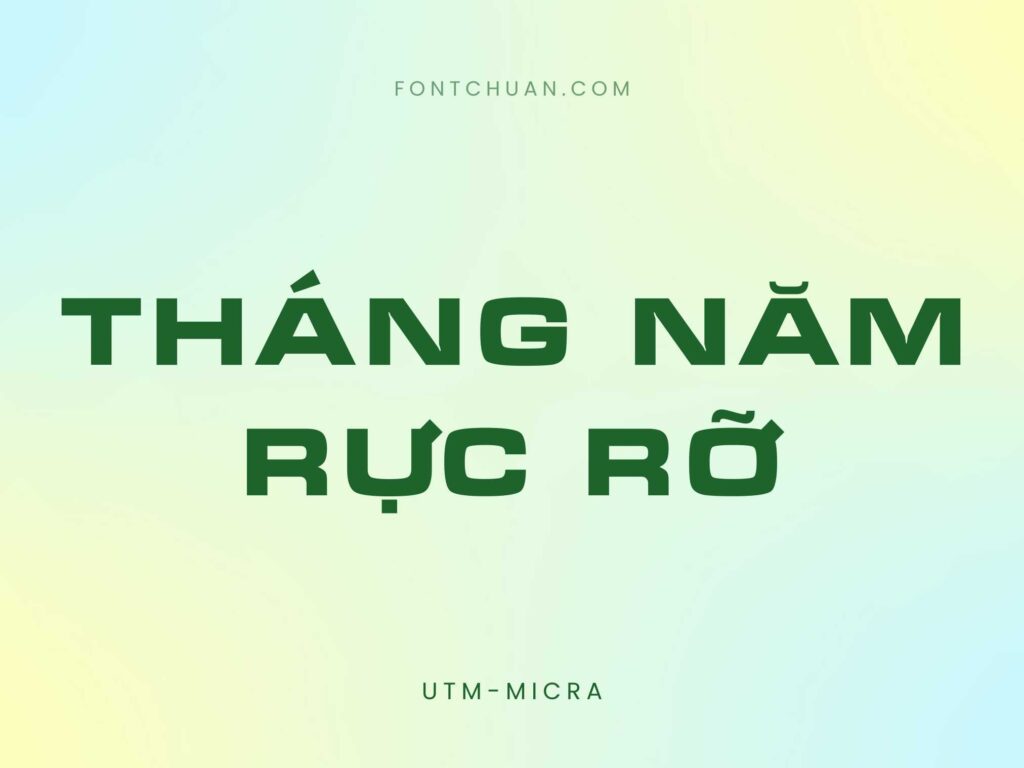
UTM Micra là một font chữ hiện đại, mang phong cách mạnh mẽ và gọn gàng, phù hợp với các thiết kế chuyên nghiệp và sáng tạo. Font này có hình thức đơn giản nhưng vẫn tạo được điểm nhấn với các đường nét rõ ràng và cân đối. Font đã được Việt hóa bởi Thiên Minh, hỗ trợ đầy đủ tiếng Việt cùng hơn 200 ngôn ngữ khác, giúp mở rộng khả năng ứng dụng trong nhiều lĩnh vực thiết kế. Thành viên của Font Chuẩn đã sưu tầm và giới thiệu font này nhằm đáp ứng nhu cầu bạn đọc, cung cấp nguồn tham khảo chất lượng và ứng dụng thực tế vào các dự án thiết kế
Về đặc điểm thiết kế, UTM Micra có cấu trúc chữ cân đối, độ dày đồng đều và phong cách tối giản. Font này phù hợp với nhiều ứng dụng như thiết kế logo, tiêu đề, poster, bảng hiệu và nội dung kỹ thuật số. Các ngành nghề như công nghệ, quảng cáo, giáo dục và thiết kế thương hiệu có thể tận dụng font này để tạo điểm nhấn và tăng tính chuyên nghiệp trong các sản phẩm thiết kế